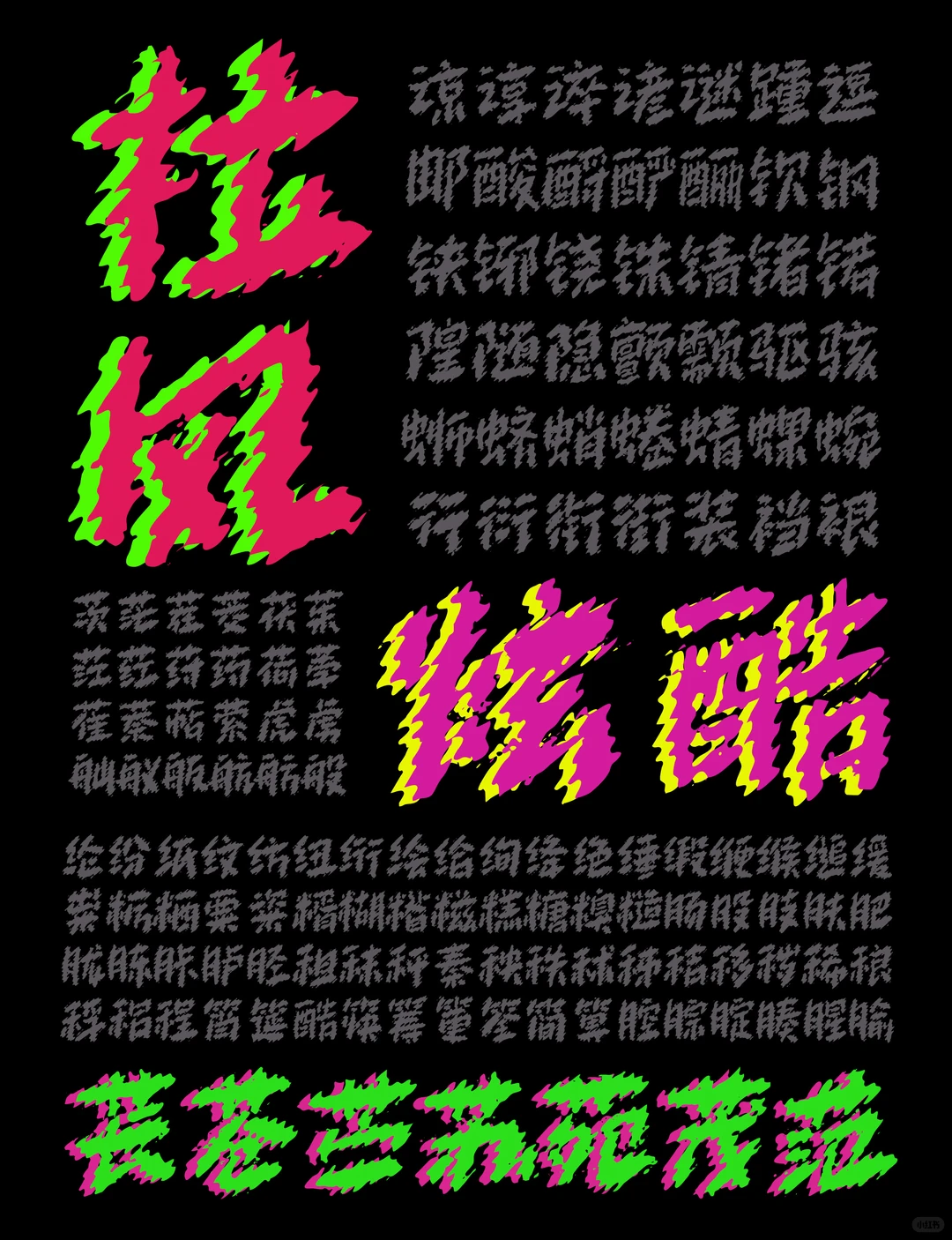
创作:小城字库 字数:7212(简体加标符) 这次确实没少花时间,前后打磨了好一阵子,哈哈,总算能把这套字库完整敲定了。这是我本人做的第一款免费商用字体,往后也会继续更新,多出几款同类型的作品。大家不管是自己日常使用还是公司项目里直接调用都没问题,适用范围挺广,授权也是长期有效的。核心只有一条,绝对禁止拿去倒卖或借转手获利,也别去拆包改形、逆向仿制,碰到违规违法的场景请自觉避开。整体走的是快速连笔的路子,笔画间透着跳跃的亮色光感,是标准的手写风格。拿来排版炫酷主题的海报、追热点的潮流物料,或者给文创周边、社媒配图加个醒目的标题装饰,效果都很出彩。